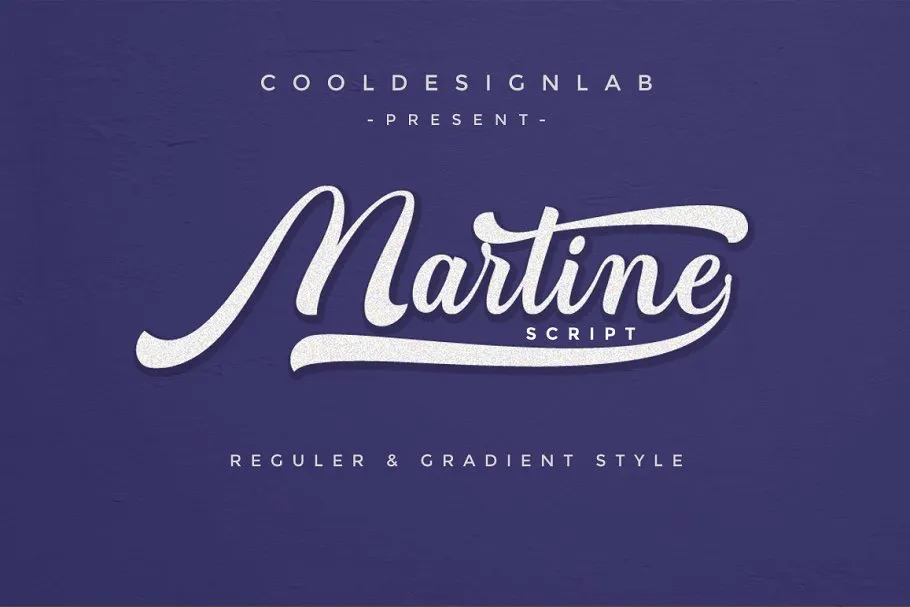
Martine Script Font
Descubra a Magia do Martine Script Font com 1001fonts! Esta fonte script é perfeita para aqueles que desejam dar um toque elegante e único aos seus projetos de design. A Martine Script Bold traz uma aparência moderna e realista, enquanto seu estilo gradiente dá mais profundidade a sua criação. Este script não só é resistente e versátil como também oferece opções para diferentes produtos de design, incluindo convites, modelos virtuais, gráficos elevados e cartões de marca. Seja você um designer profissional ou um iniciante, Martine Script está aqui para fornecer uma solução de fontes que tornará seu trabalho ainda mais especial. Experimente hoje mesmo e descubra o brilho único dessa fonte!